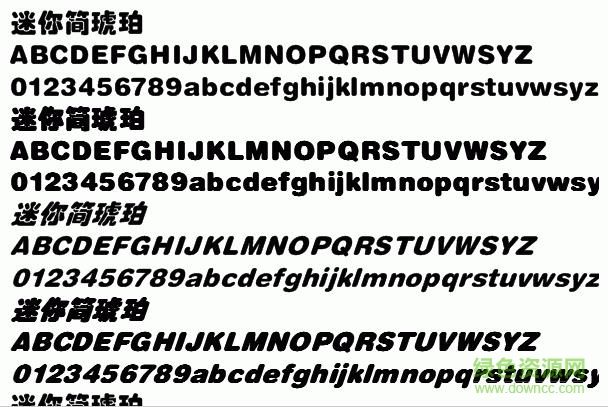
迷你簡琥珀字體是非常好看的琥珀字體,用戶能夠?qū)ζ溥M(jìn)行加粗,傾斜,變換等眾多便捷操作從而實現(xiàn)更加多彩的文字變現(xiàn)形式,運用到各類生活與工作文件編輯中廣受使用!需要的用戶快到綠色資源網(wǎng)下載體驗吧!
迷你簡琥珀字體有著所以琥珀字體的特征,比較精,而且也比較圓潤,哈哈,也就是通常所說的富態(tài)相,還是生活中用的比較多的字體喔。